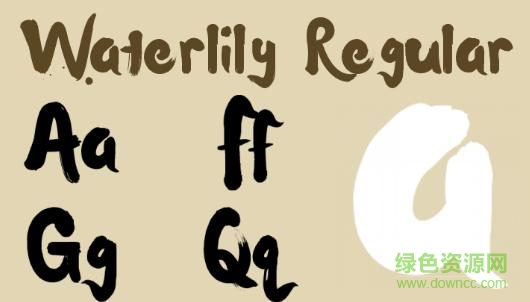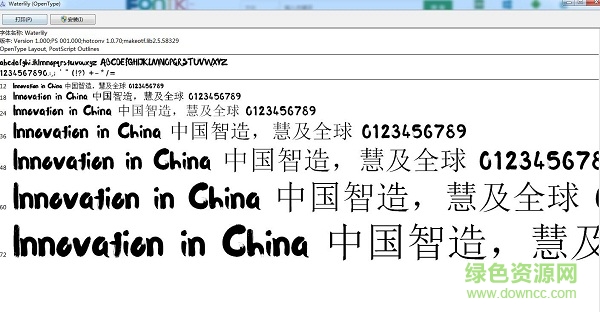
waterlily字體是一款漂亮的英文書法字體,字體線條像是水墨勾勒出來的一樣黑白分明,給人流暢又灑脫的視覺感受,具有藝術(shù)氣息,歡迎大家在本站免費(fèi)下載!
英文字體(包括漢語拼音)的設(shè)計(jì),可分為兩種基本字體,即書法體和裝飾體。
裝飾字體的設(shè)計(jì),應(yīng)用范圍非常廣泛,它的特征是在一定程度上擺脫了印刷字體的字形和筆劃的約束,根據(jù)品牌或企業(yè)經(jīng)營(yíng)性質(zhì)的需要進(jìn)行設(shè)計(jì),達(dá)到加強(qiáng)文字的精神含義和富于感染力的目的。
書法體的設(shè)計(jì)雖然很有個(gè)性、很美觀,但識(shí)別性差,用于標(biāo)識(shí)設(shè)計(jì)時(shí)的不常見,常見的情況是用于人名,或非常簡(jiǎn)短的商品名稱。